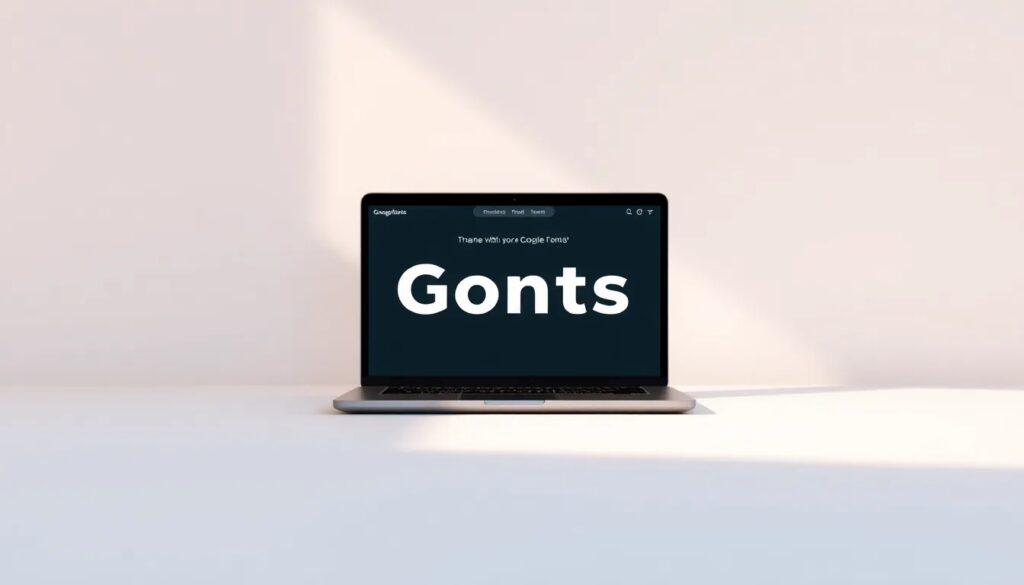
Google Fonts CSS: cómo utilizarlas en tu sitio web
Las Google Fonts son una herramienta increíble que permite a los diseñadores y desarrolladores web enriquecer sus proyectos con más de 1000 fuentes gratuitas. En este artículo, exploraremos cómo incorporar estas fuentes en tu sitio web utilizando Google Fonts CSS, así como las mejores prácticas para optimizar su uso.
Desde la personalización tipográfica hasta la aplicación de efectos visuales, descubre cómo las fuentes de Google pueden transformar el diseño de tu página. Vamos a sumergirnos en los aspectos más destacados.
Cómo usar Google Fonts en tu proyecto
Integrar Google Fonts en tu proyecto es un proceso sencillo. Solo necesitas seguir unos pocos pasos básicos. Primero, visita la página de Google Fonts y selecciona las fuentes que más te gusten.
Una vez elegidas las fuentes, deberás copiar el enlace proporcionado y pegarlo en la sección `` de tu archivo HTML. Este enlace te permite cargar las fuentes desde el servidor de Google cada vez que alguien visita tu sitio.
En tu archivo CSS, especifica la fuente deseada para los elementos HTML. Por ejemplo:
body {
font-family: 'Roboto', sans-serif;
}
¿Qué son las fuentes Google?
Las fuentes Google son colecciones de tipografías que están disponibles de forma gratuita para su uso en sitios web y aplicaciones. Estas fuentes están optimizadas para la web y son fáciles de personalizar.
Proporcionan opciones versátiles que se adaptan a diferentes estilos y necesidades de diseño. Desde fuentes serif hasta sans-serif, las opciones son prácticamente infinitas.
Además, Google Fonts se actualiza regularmente, lo que significa que siempre hay nuevas fuentes para explorar. Esto permite que los diseñadores mantengan su trabajo fresco y actualizado.
¿Cómo combinar varias fuentes con Google Fonts?
Combinar varias fuentes en un mismo sitio web puede ser un desafío, pero con Google Fonts es bastante sencillo. Una vez que selecciones las fuentes deseadas, simplemente sepáralas con un pipe (`|`) en tu enlace. Por ejemplo:
Al usar múltiples fuentes, es crucial mantener una buena legibilidad. Generalmente es recomendable combinar una fuente más decorativa con una más sencilla para asegurar que el contenido sea fácil de leer.
- Usa una fuente grande y llamativa para los títulos.
- Selecciona una fuente más simple para los párrafos de texto.
- Evita usar más de tres fuentes diferentes en una misma página.
¿Qué efectos visuales se pueden aplicar a las fuentes?
Una de las características más atractivas de Google Fonts CSS es la posibilidad de aplicar efectos visuales a las fuentes. Puedes añadir sombras, resaltar texto o incluso crear animaciones.
Algunos efectos populares incluyen:
- Sombras: Puedes agregar sombras a las fuentes usando la propiedad `text-shadow` en CSS.
- Brillo: Usa `text-shadow` para crear un efecto de neón.
- Transformaciones: Aplica rotaciones o escalas en el texto.
Estos efectos pueden hacer que tu texto sea más dinámico y atractivo para los visitantes, pero es importante no exagerar para no comprometer la legibilidad.
¿Cómo estilizar fuentes usando CSS?
El estilo de las fuentes en CSS es fundamental para dar personalidad a tu sitio web. Puedes cambiar el tamaño, el estilo y el peso de las fuentes utilizando propiedades CSS como:
font-size: 16px;
font-weight: bold;
font-style: italic;
Por ejemplo:
h1 {
font-family: 'Montserrat', sans-serif;
font-size: 2em;
font-weight: bold;
}
Asegúrate de definir una fuente de respaldo en caso de que la fuente principal no se cargue. Esto es crítico para mantener una buena experiencia de usuario.
¿Cuáles son algunas fuentes populares de Google?
La variedad de fuentes en Google Fonts es extensa, pero hay ciertas tipografías que se destacan por su popularidad y efectividad:
- Roboto: Ideal para una lectura clara y moderna.
- Open Sans: Una fuente amigable para interfaces web.
- Montserrat: Perfecta para títulos llamativos y diseñados.
- Lora: Excelente opción para un estilo más literario.
- Oswald: Una opción para un diseño impactante y audaz.
Elegir la fuente correcta puede influir significativamente en la percepción del contenido por parte del usuario. ¡Experimenta y encuentra la combinación perfecta para tu estilo!
Para obtener más inspiración sobre Google Fonts CSS y su uso en el diseño web, aquí tienes un interesante vídeo que muestra ejemplos prácticos de su implementación:
Mejores prácticas para usar Google Fonts en diseño web
- Selecciona solo las fuentes que realmente necesitas para evitar tiempos de carga innecesarios.
- Establece una fuente de respaldo en tu CSS para mantener la legibilidad.
- Revisa la carga de fuentes en dispositivos móviles para mejorar la experiencia del usuario.
Al seguir estos consejos, puedes garantizar que tu uso de Google Fonts mejore la estética y la funcionalidad de tu sitio web sin comprometer el rendimiento.